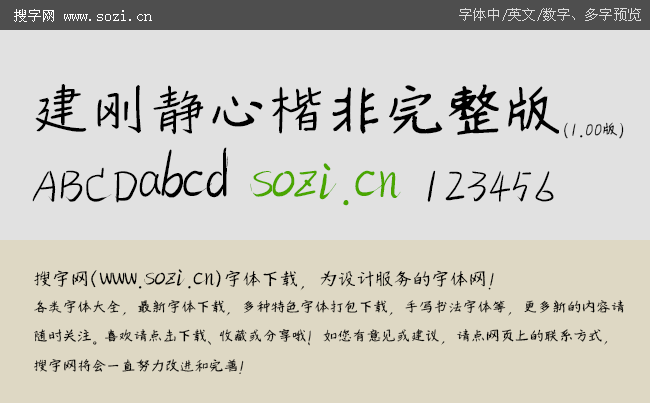
建剛精心楷非完整版
搜字網(wǎng)提供一款建剛精心楷非完整版中文書法字體下載,建剛精心楷非完整版是一款硬筆書法字體,該字體非常細(xì)膩,有點(diǎn)類似于卡通效果,并且整體效果非常不錯(cuò),可以應(yīng)用于廣告設(shè)計(jì)、名片設(shè)計(jì)、包裝印刷、產(chǎn)品設(shè)計(jì)等方面,有喜歡的朋友可免費(fèi)下載收藏。